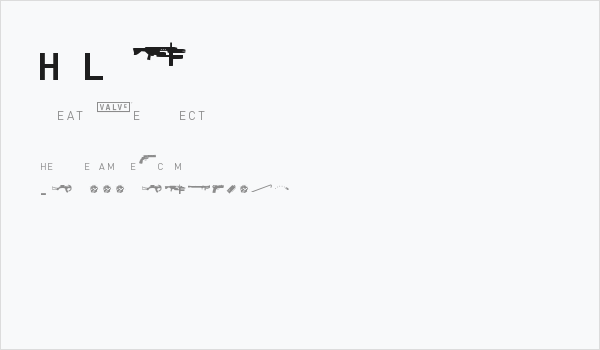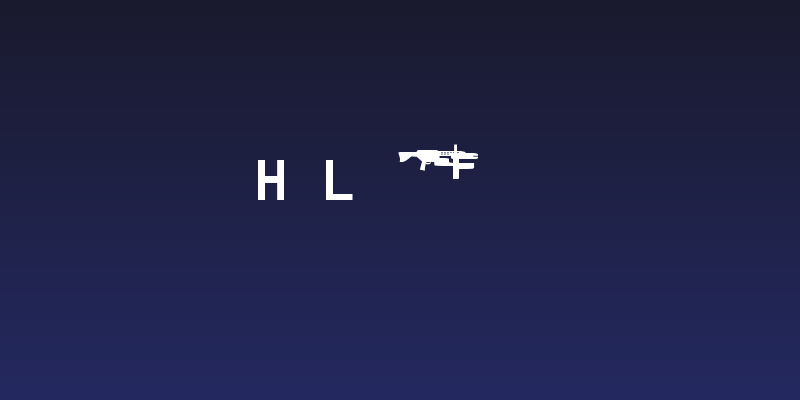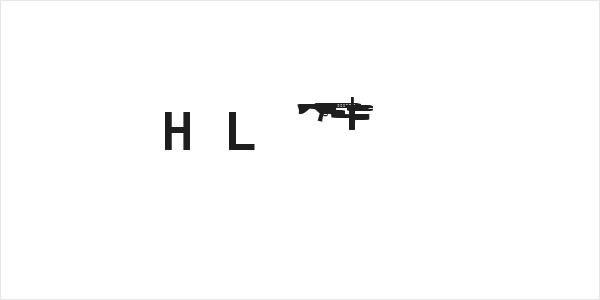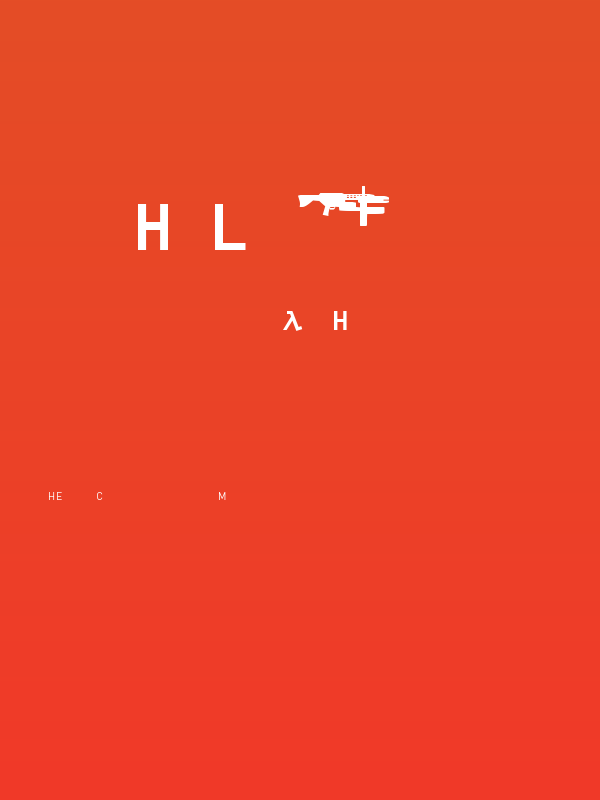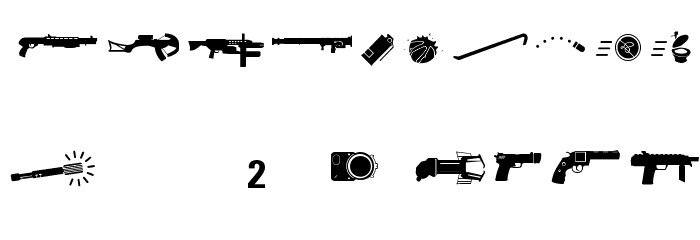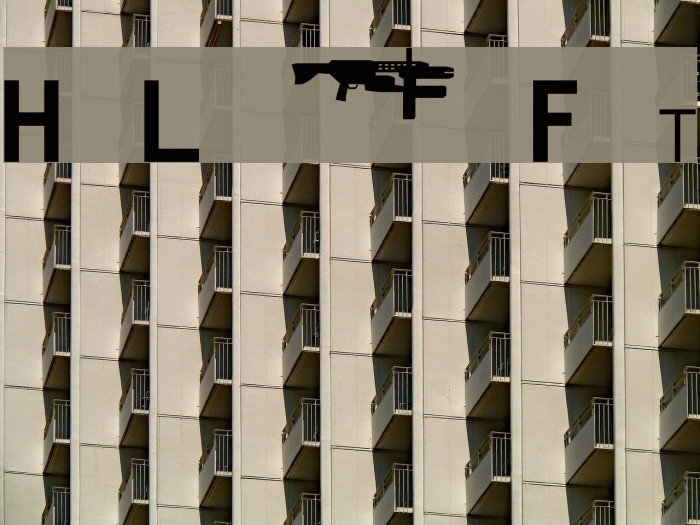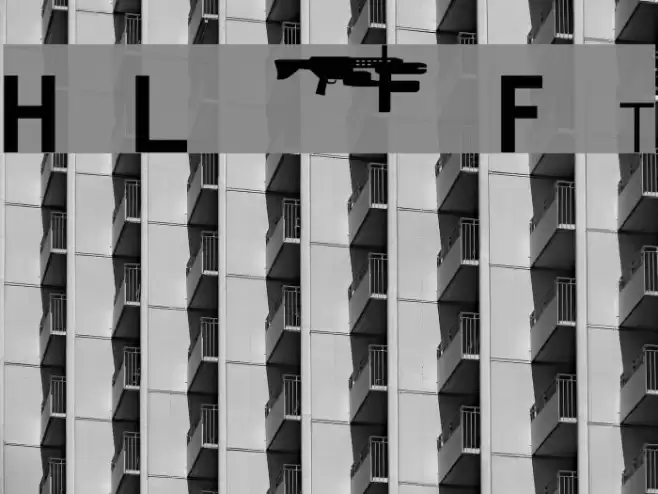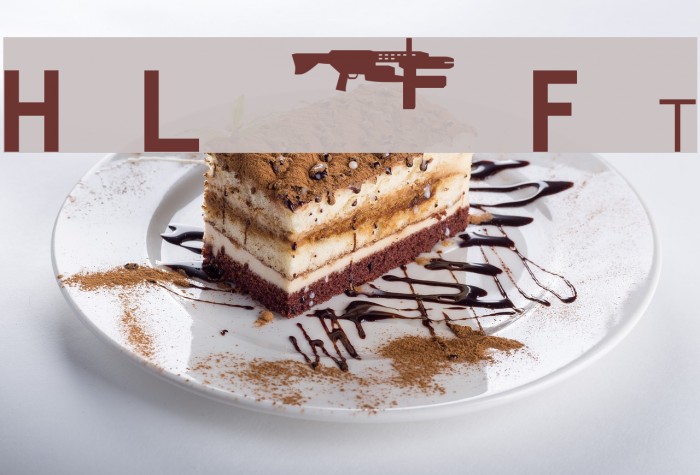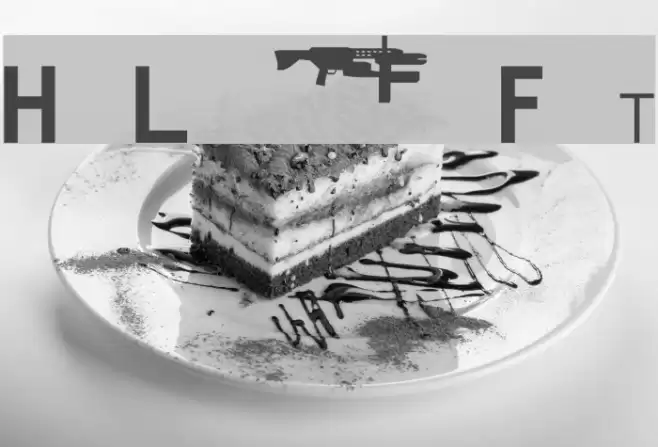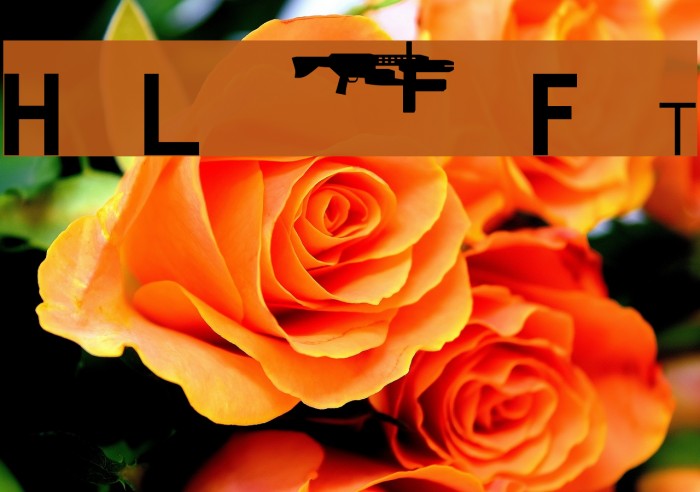
HL2MP Font
| Stil general | Thematic, Game-related |
| Caz de utilizare | Themed graphics, Merchandise design |
| Proiecte propuse | This set of symbols could be used for themed graphic design projects, game-related artwork, or merchandise design. |